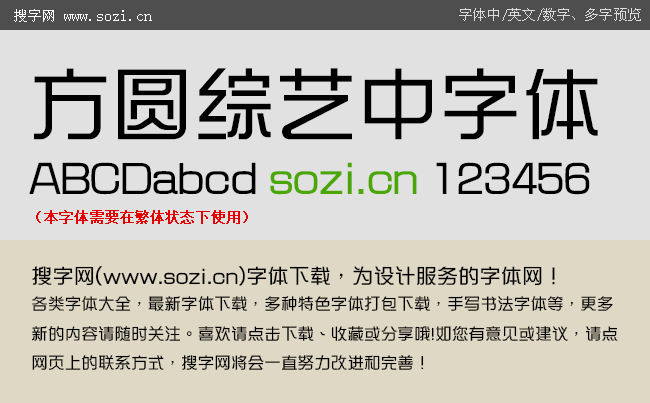
方圓綜藝中字體
搜字網(wǎng)提供一款方圓綜藝中字體下載。綜藝體是黑體的一種變體,也是藝術(shù)字的一種。特點(diǎn)是筆劃更粗,盡量將空間充滿。同時(shí)為了美觀,對(duì)拐彎處的處理較為圓潤(rùn)。此款綜藝體粗細(xì)適中,適用于廣告、報(bào)刊等的標(biāo)題及海報(bào)展板等設(shè)計(jì)場(chǎng)合使用。